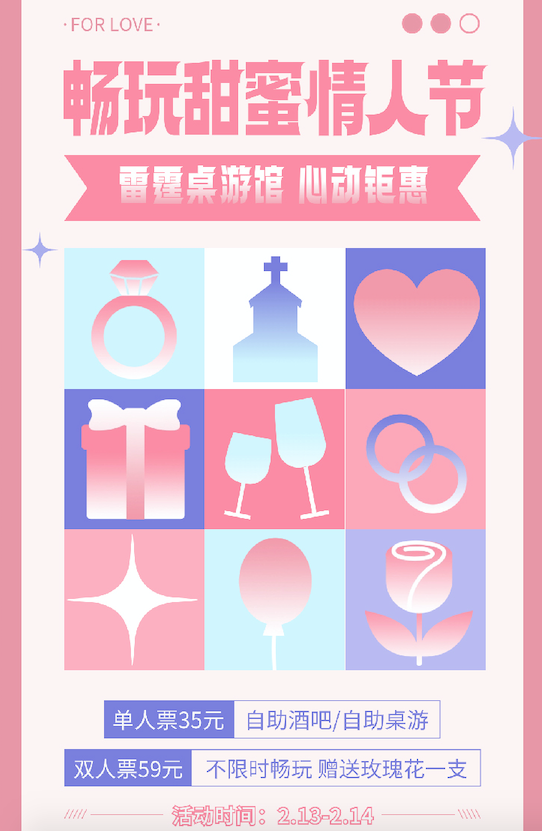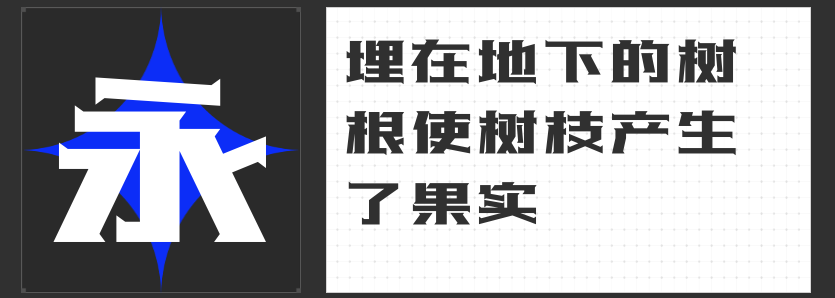
刘兵克字库精选:四款风格化字体,为设计注入独特张力
在视觉设计领域,字体的选择是传递品牌气质与情感的关键。刘兵克字库(励字造梦共创字库旗下品牌)以创新设计为核心,推出多款兼具实用性与艺术性的字体。以下四款字体各具特色,能为不同场景的设计注入鲜明个性。
1. 高手兵克锐黑体
高手兵克锐黑体以“几何张力”为设计语言,四边直角的硬朗结构奠定现代感基调,而笔画末端的向上或向下三角装饰,则成为其视觉符号。这种“尖锐”与“秩序”的碰撞,让字体在科技、运动或潮牌设计中极具辨识度。无论是海报标题的冲击力,还是UI界面的极简表达,锐黑体都能以精准的几何语言传递先锋态度。
2. 高手兵克逍遥体
高手兵克逍遥体以“潇洒不羁”为灵魂,手写笔触的粗细变化与连笔处理,赋予文字呼吸感与动态美。其笔画起收笔干脆利落,无多余修饰,仿佛书写者一气呵成的情绪流露。这款字体适合文化创意、文艺活动或生活方式品牌,搭配水墨背景或手绘插画,能瞬间营造随性洒脱的视觉氛围,让设计更贴近人文温度。
3. 高手兵克高雅宋
高手兵克高雅宋从传统宋体中提炼精髓,字形修长挺拔,笔画粗细对比鲜明,既有古典书卷气,又融入现代审美。横画末端保留宋体“三角装饰”,竖画则以简洁线条收尾,刚柔并济。这款字体适用于高端化妆品、艺术展览或文化出版物,其优雅气质能提升设计质感,传递精致而内敛的品牌调性。
4. 高手兵克雷霆体
高手兵克雷霆体以“圆润不失棱角”为设计巧思,笔画四周采用圆角处理,赋予字体亲和力,而外轮廓的尖角则打破柔和感,形成反差萌。这种“外柔内刚”的视觉效果,使其在儿童品牌、游戏界面或年轻化设计中极具表现力。无论是卡通IP形象搭配,还是动态海报标题,雷霆体都能以趣味感与辨识度抓住受众眼球。
刘兵克字库的这四款字体,从现代几何到手写韵律,从古典优雅到趣味反差,覆盖多元设计场景。它们不仅是工具,更是创意的延伸——锐黑体的锋芒、逍遥体的自由、高雅宋的优雅、雷霆体的趣味,皆可成为设计师笔下的“视觉符号”,让作品在同质化中脱颖而出。